Top 15 font chữ cho phòng gym, fitness, yoga và thương hiệu thể hình
Gợi ý 15 font TH Việt hóa cho phòng gym, fitness, yoga và thương hiệu thể hình: mạnh mẽ, hiện đại, dễ đọc trên bảng hiệu, poster và social.
Font chữ cho phòng gym, fitness, yoga và thương hiệu thể hình cần truyền được năng lượng ngay từ cái nhìn đầu tiên. Một logo gym không nên quá mềm nếu định vị là mạnh mẽ, hiệu suất cao. Một poster lớp yoga cũng không nên quá nặng nếu thương hiệu muốn tạo cảm giác thư giãn, cân bằng và chăm sóc cơ thể.
Điểm khó là ngành fitness không chỉ có một phong cách. Gym sức mạnh cần font chắc, dày, tốc độ. Boxing, CrossFit, calisthenics hoặc bootcamp cần font có lực. Fitness lifestyle có thể hiện đại, gọn và sạch hơn. Yoga, pilates, wellness lại cần chữ nhẹ, tinh tế và dễ thở.
Bài viết này gợi ý 15 font TH Việt hóa phù hợp cho bảng hiệu phòng gym, logo PT, áo đồng phục, poster lớp học, banner quảng cáo, landing page hội viên và các ấn phẩm social media tiếng Việt.
Cách chọn font cho thương hiệu gym và fitness
Xác định tính cách thương hiệu trước khi chọn font
Nếu phòng gym định vị là mạnh mẽ, nam tính, thi đấu hoặc hiệu suất cao, hãy ưu tiên font dày, chắc, có góc cạnh hoặc cảm giác tốc độ. Nếu thương hiệu hướng đến fitness lifestyle, hãy chọn font sans-serif hiện đại, sạch và dễ đọc. Nếu là yoga hoặc wellness, font nên mềm hơn, không quá nặng và có nhiều khoảng thở.
Kiểm tra khả năng đọc trên bảng hiệu và social media
Font gym thường xuất hiện trên bảng hiệu, áo thun, poster lớp học, story, banner sale và ảnh quảng cáo. Vì vậy, hãy kiểm tra ở nhiều kích thước: logo nhỏ trên avatar, tiêu đề lớn trên poster, chữ trên áo và CTA trên điện thoại.
Không dùng font quá mạnh cho mọi dòng chữ
Một font cực mạnh có thể hợp cho logo hoặc headline, nhưng không nên dùng cho lịch tập, giá gói, địa chỉ, hotline hoặc mô tả lớp học. Các thông tin này cần đọc nhanh. Cách an toàn là dùng font mạnh cho điểm nhấn và một font sans-serif rõ cho phần còn lại.
Top 15 font TH cho phòng gym, fitness và yoga
1. TH Rakend - font mạnh mẽ cho gym, xây dựng cơ bắp và thương hiệu nam tính
TH Rakend là lựa chọn rất hợp cho phòng gym sức mạnh, boxing, bootcamp, thương hiệu thực phẩm bổ sung, áo đồng phục đội nhóm hoặc poster thử thách 30 ngày. Font có cảm giác chắc, thẳng và có lực, giúp thương hiệu nhìn mạnh mẽ ngay.
Bạn có thể dùng TH Rakend cho logo, headline banner, bảng hiệu hoặc tên chương trình như "Thử thách giảm mỡ", "Sức mạnh bứt phá", "Tập luyện nghiêm túc". Phần lịch tập và giá gói nên dùng font phụ rõ hơn.
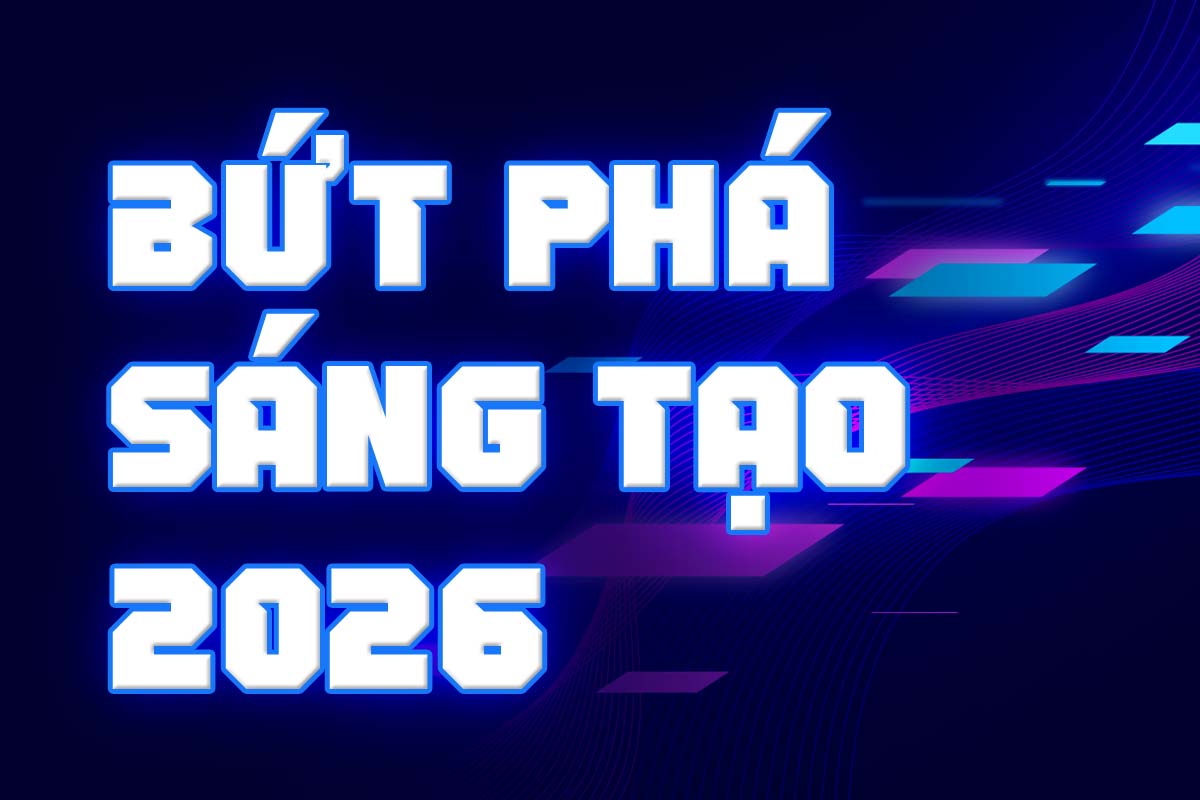
2. TH Geardive - font tốc độ cho fitness, sports và esports gym
TH Geardive có dáng nghiêng, đường cắt sắc và cảm giác tốc độ. Font phù hợp với gym hiện đại, studio HIIT, câu lạc bộ chạy bộ, thương hiệu thể thao, giải đấu fitness hoặc banner quảng cáo có tinh thần thi đấu.
Với TH Geardive, hãy dùng trên nền tương phản mạnh và tiêu đề ngắn. Font có năng lượng cao, nên rất hợp với các thông điệp như "Burn Fat", "Speed Training", "Bứt tốc", "Fit Challenge".
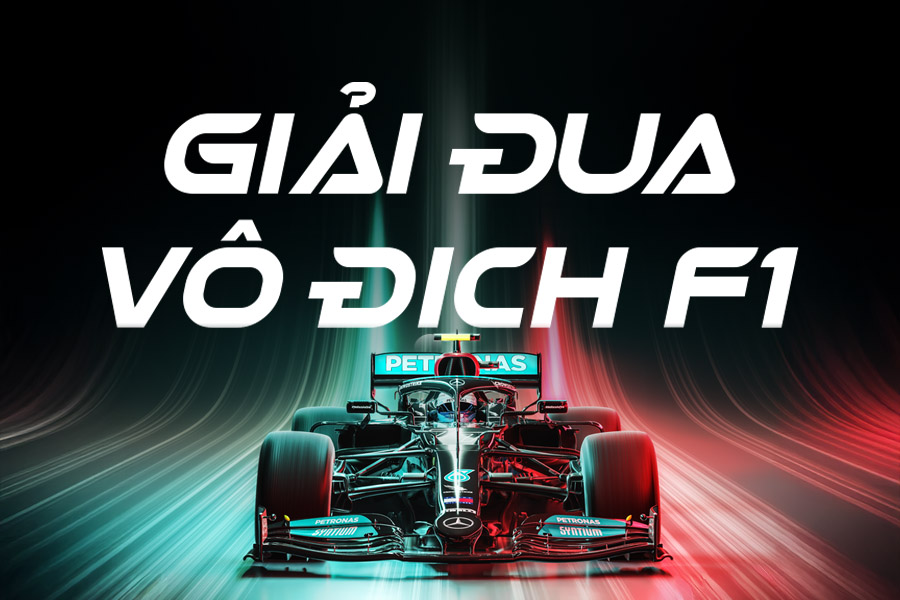
3. TH Glister - condensed cứng cáp cho poster lớp học và banner ngang
TH Glister có dáng condensed, nét dày và gọn, phù hợp khi thiết kế poster lớp học, banner ngang, thumbnail video hoặc bảng lịch tập cần tiêu đề lớn nhưng không có nhiều không gian. Font giúp chữ nhìn mạnh mà vẫn tiết kiệm chiều rộng.
Bạn có thể dùng TH Glister cho tên lớp như "Cardio Burn", "Strength Class", "Boxing Night", "Full Body Workout". Vì chữ nén, hãy tăng khoảng cách dòng nếu tiêu đề có dấu tiếng Việt dày.
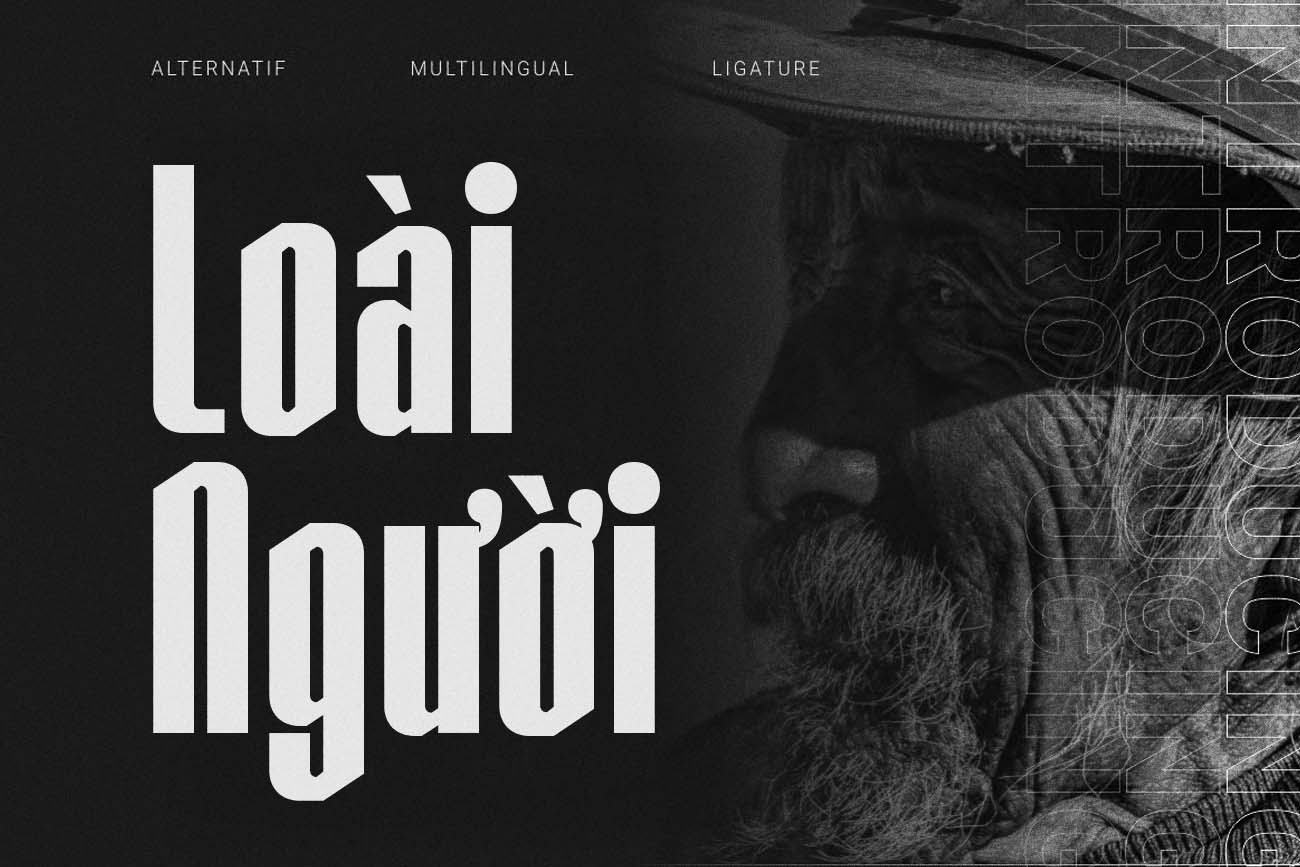
4. TH Infinity - font display cứng cáp cho thương hiệu năng động
TH Infinity hợp với thương hiệu gym, thiết bị tập luyện, sportswear, giải đấu, trung tâm thể hình hoặc các chiến dịch cần cảm giác bền chắc. Font có hình khối mạnh, dễ dùng cho logo chữ, poster và key visual.
Khi dùng TH Infinity cho bảng hiệu hoặc áo thun, hãy giữ bố cục đơn giản. Font đã đủ lực, không cần quá nhiều viền, bóng hoặc hiệu ứng kim loại.
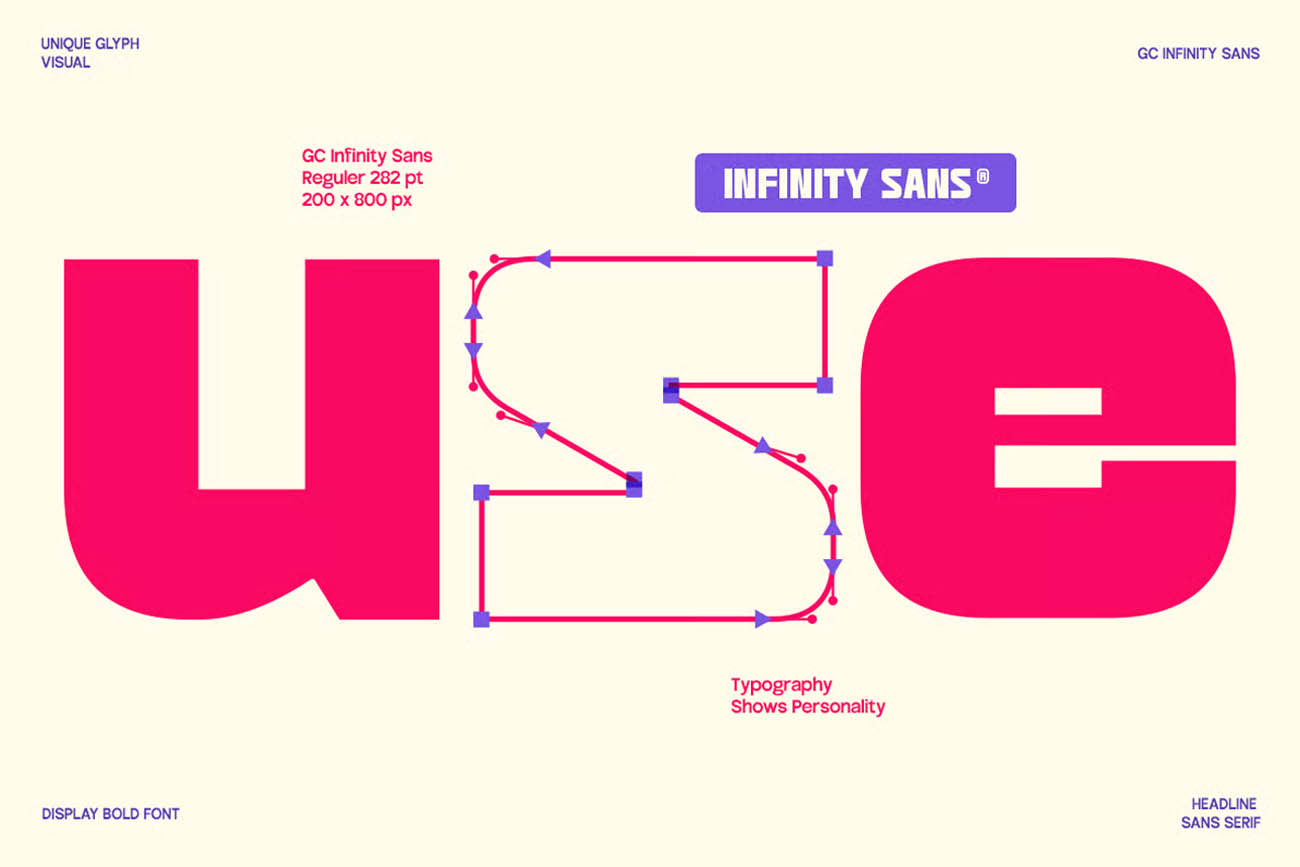
5. TH Army Rangers - stencil cho bootcamp, outdoor và tactical training
TH Army Rangers phù hợp với bootcamp, outdoor training, thử thách sức bền, lớp kỹ năng sinh tồn, thương hiệu tactical fitness hoặc poster sự kiện có tính kỷ luật. Font stencil tạo cảm giác mạnh, nghiêm và khác biệt.
Bạn nên dùng font này cho headline hoặc tên chương trình. Nếu dùng cho toàn bộ lịch tập, font sẽ hơi nặng. Hãy phối với font phụ gọn để thông tin được đọc nhanh.
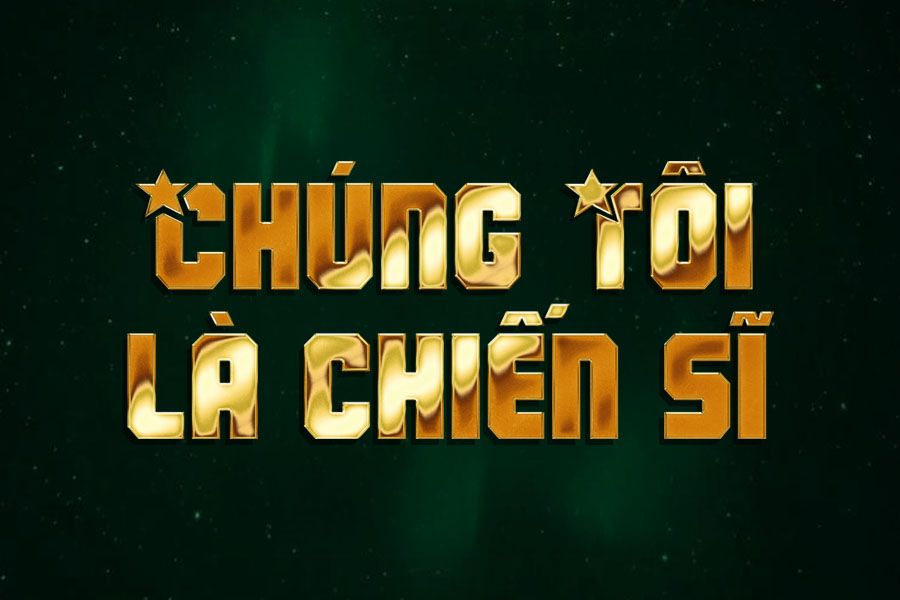
6. TH Jurasick - font thể thao cho hoạt động năng lượng cao
TH Jurasick có cảm giác khỏe, vui và năng động, phù hợp với poster hoạt động thể chất, sự kiện ngoài trời, câu lạc bộ vận động, lớp thiếu niên, giải đấu nội bộ hoặc thương hiệu fitness trẻ trung.
Font này không quá nghiêm như nhóm stencil hay công nghệ, nên hợp khi phòng tập muốn tạo cảm giác gần gũi hơn. Hãy dùng cho headline và phối cùng màu xanh, cam, vàng, đen hoặc các mảng màu năng lượng.
Xem mẫu và tải font TH Jurasick Việt hóa.
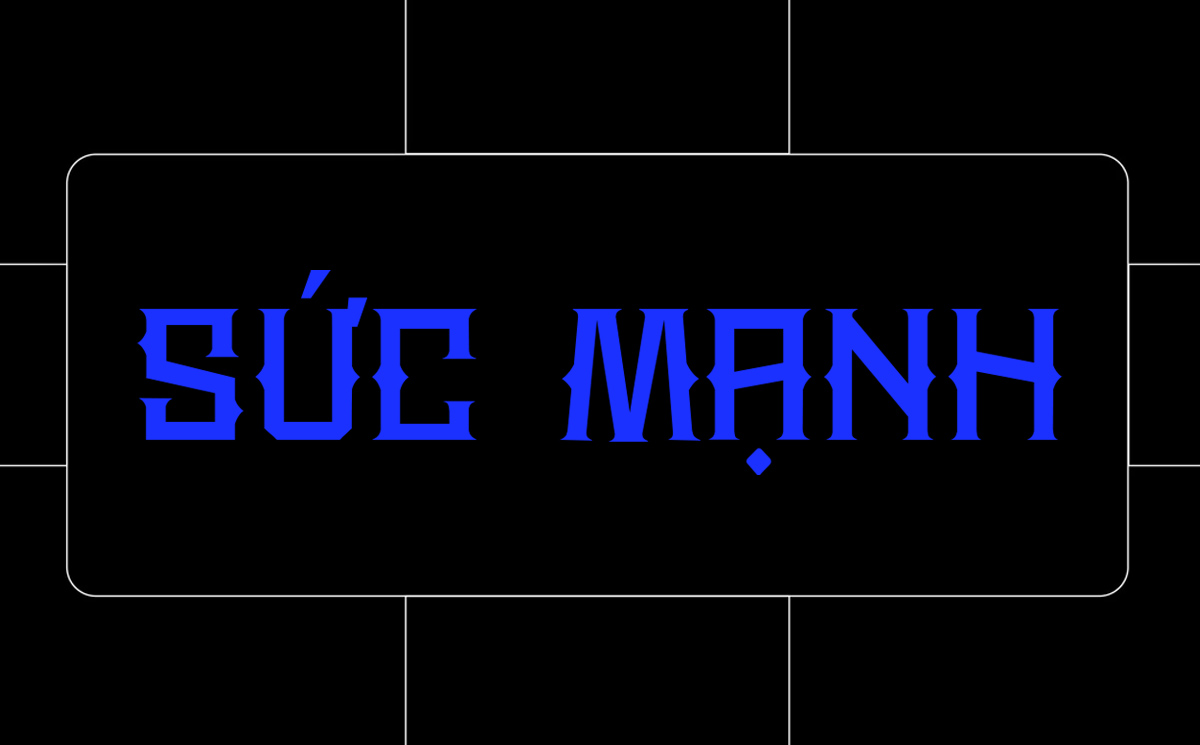
7. TH Cungcap 10 - font game mạnh cho thử thách và giải đấu
TH Cungcap 10 có phong cách game và thể thao mạnh, phù hợp với giải đấu gym nội bộ, thử thách plank, challenge giảm mỡ, poster esports fitness hoặc lớp dành cho nhóm trẻ. Font giúp thiết kế có cảm giác cạnh tranh và hiện đại.
Bạn nên dùng TH Cungcap 10 cho tên event, bảng xếp hạng, huy hiệu hoặc tiêu đề social post. Phần mô tả điều kiện tham gia nên dùng font dễ đọc hơn.
Xem mẫu và tải font TH Cungcap 10 Việt hóa.
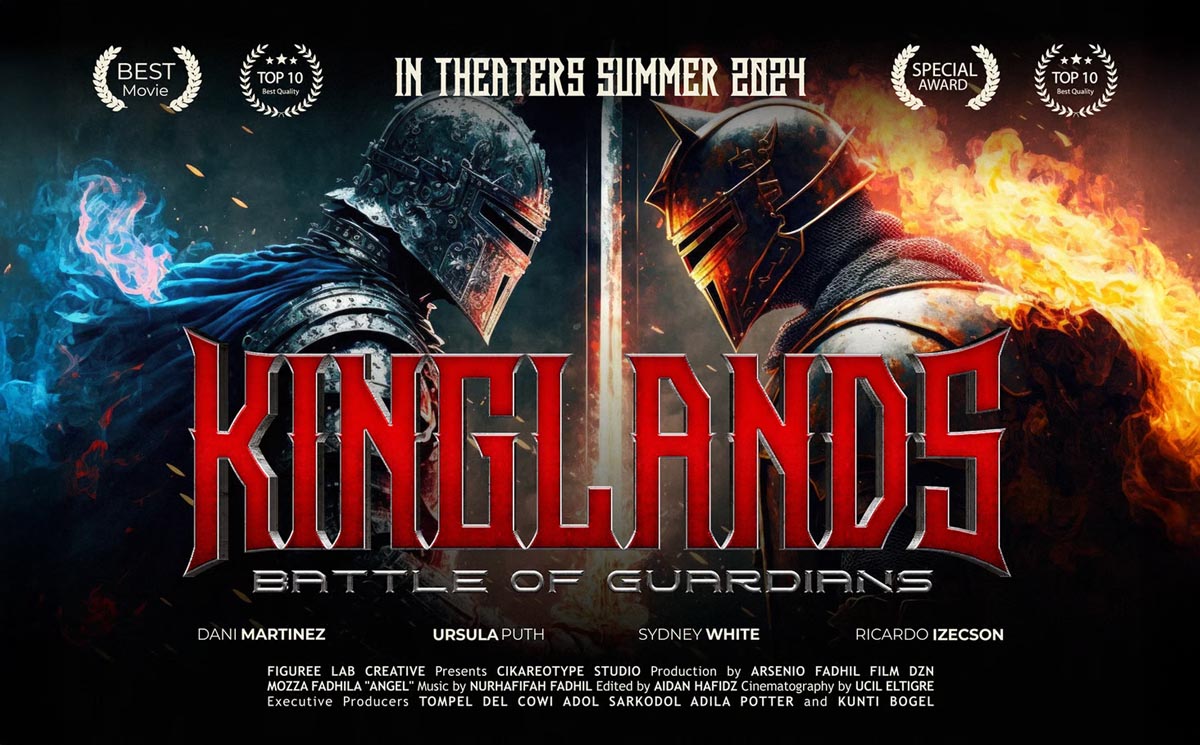
8. TH Gyokz - font công nghệ cho fitness app và phòng gym hiện đại
TH Gyokz hợp với app fitness, phần mềm quản lý phòng gym, smart gym, thiết bị đo sức khỏe, chương trình training online hoặc thương hiệu thể hình định vị công nghệ. Font có cảm giác sắc, hiện đại và tương lai.
Khi dùng TH Gyokz, hãy giữ nền sạch và thông tin gọn. Font này rất hợp với các cụm như "Smart Training", "AI Coach", "Tracking Progress" hoặc "Dữ liệu tập luyện".
Xem mẫu và tải font TH Gyokz Việt hóa.
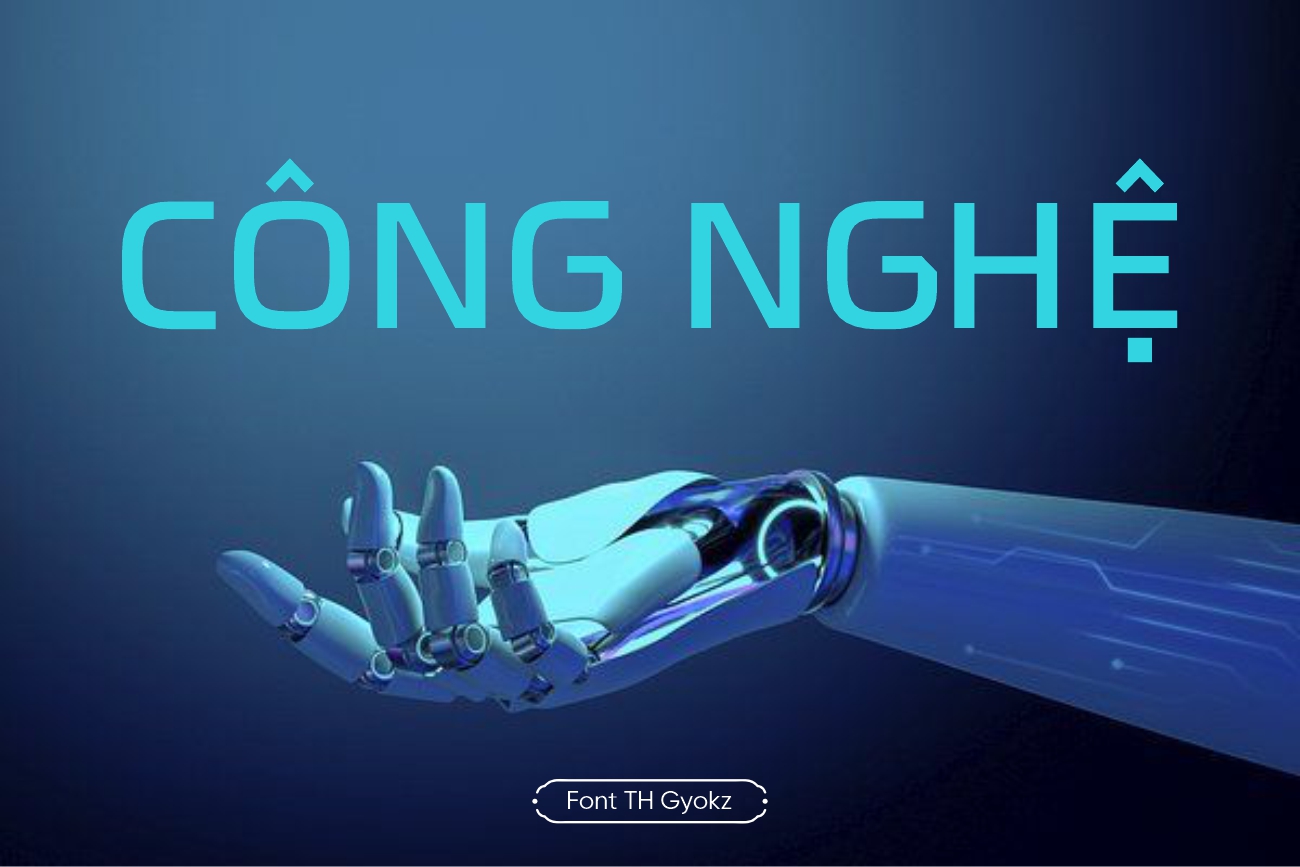
9. TH Seona Display - font digital cho gym online và sản phẩm số
TH Seona Display phù hợp với landing page gym online, khóa học fitness, app tracking, thiết bị wearable hoặc banner digital. Font có hình khối công nghệ, giúp thiết kế nhìn hiện đại hơn.
Bạn có thể dùng TH Seona Display cho headline web, banner quảng cáo và thumbnail video. Với nội dung dài, hãy phối thêm font sans-serif trung tính để tránh mỏi mắt.
Xem mẫu và tải font TH Seona Display Việt hóa.
10. TH Legacy Sans - font phụ rõ ràng cho lịch tập và bảng giá
TH Legacy Sans là lựa chọn tốt cho phần thông tin cần đọc nhanh: lịch lớp, bảng giá hội viên, nội quy phòng tập, form đăng ký, landing page và app. Không phải mọi chữ trong thiết kế gym đều cần mạnh; đôi khi font rõ mới là thứ giúp khách hàng quyết định.
Bạn có thể dùng TH Legacy Sans làm font phụ cho TH Rakend, TH Geardive, TH Glister hoặc TH Kinetic Motion. Cách phối này giúp thiết kế vừa có lực vừa dễ đọc.
Xem mẫu và tải font TH Legacy Sans Việt hóa.
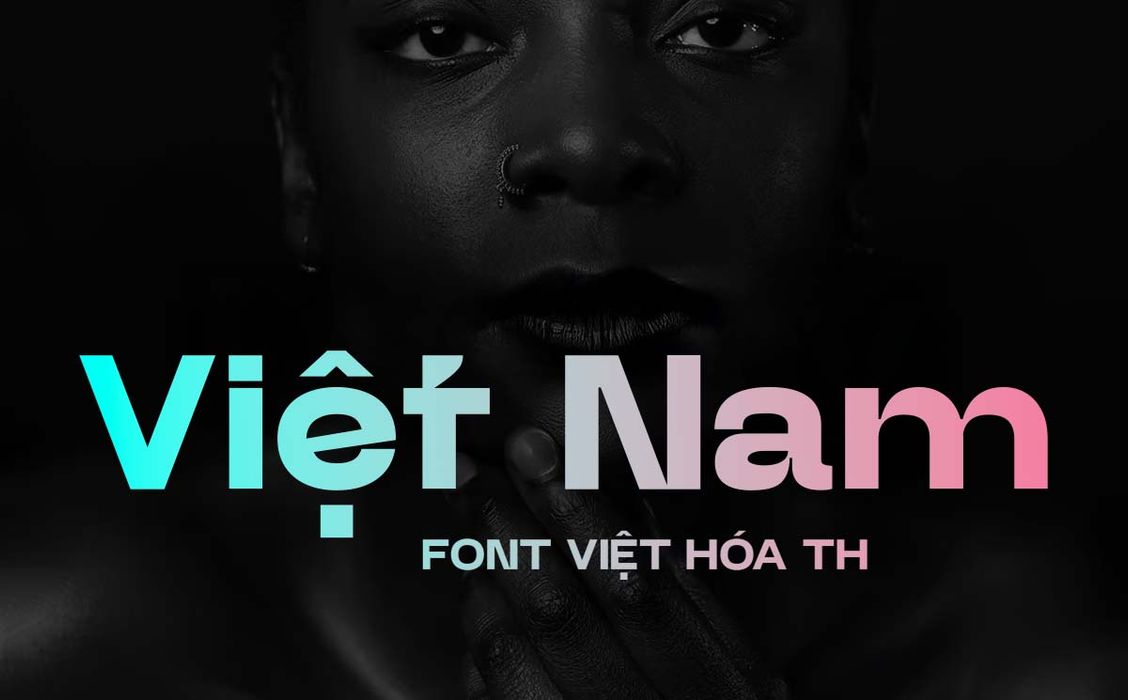
11. TH Guton - bộ font đa weight cho thương hiệu fitness chuyên nghiệp
TH Guton có nhiều style, phù hợp với bộ nhận diện fitness cần hệ thống chữ ổn định: headline, subheading, nội dung, nhãn giá, nút CTA và tài liệu hội viên. Font không quá trang trí nên dùng được trong nhiều ngữ cảnh.
Nếu bạn đang làm brand kit cho phòng gym, TH Guton có thể làm font chính cho hệ thống, sau đó thêm một font display mạnh cho campaign hoặc poster.
Xem mẫu và tải bộ font TH Guton Việt hóa.
12. TH Grotley - luxury sans-serif cho yoga, pilates và boutique fitness
TH Grotley phù hợp với boutique fitness, pilates, yoga studio, wellness center hoặc phòng tập cao cấp cần cảm giác tinh tế. Font vẫn là sans-serif nên đủ gọn, nhưng có sắc thái luxury hơn nhóm font kỹ thuật.
Bạn có thể dùng TH Grotley cho logo chữ, headline website, brochure dịch vụ và bảng giá gói hội viên premium. Bảng màu nên nhẹ hơn: kem, đen, trắng, xanh sage, nâu nhạt hoặc vàng champagne.
Xem mẫu và tải font TH Grotley Việt hóa.
13. TH Retalin Regular - font mềm cho yoga, spa fitness và wellness
TH Retalin Regular hợp với yoga, pilates, spa fitness, lớp thở, thiền, chăm sóc cơ thể hoặc thương hiệu wellness. Font mềm hơn nhóm thể thao mạnh, giúp thiết kế tạo cảm giác thư giãn và thân thiện.
Khi dùng TH Retalin Regular, hãy ưu tiên bố cục thoáng, ảnh sáng và màu dịu. Font phù hợp với headline, tên lớp, quote hoặc banner nhẹ nhàng. Phần lịch tập vẫn nên dùng font phụ rõ.
Xem mẫu và tải font TH Retalin Regular Việt hóa.
14. TH Valoer - font thẩm mỹ cho wellness và lifestyle fitness
TH Valoer phù hợp với wellness, yoga cao cấp, studio chăm sóc vóc dáng, thương hiệu beauty fitness hoặc lifestyle coaching. Font có cảm giác thẩm mỹ, tinh tế và nhẹ hơn các font gym truyền thống.
Bạn nên dùng TH Valoer cho headline, tên dịch vụ, poster lớp đặc biệt hoặc landing page giới thiệu gói hội viên. Với thông tin chi tiết, hãy phối thêm TH Legacy Sans hoặc TH Guton.
Xem mẫu và tải font TH Valoer Việt hóa.
Phông chữ sport tốc độ TH Myahewa Regular
TH Myahewa Regular là một phông chữ sans serif mang phong cách thể thao mạnh mẽ, gắn liền với tinh thần tốc độ, sức mạnh và sự quyết đoán. Với thiết kế hiện đại, đường nét dứt khoát và tỷ lệ chữ năng động, Myahewa mang đến một diện mạo đậm chất hành động – phù hợp cho các dự án branding thể thao, poster sự kiện, banner giải đấu hay giao diện truyền thông liên quan đến vận động.
Xem và tải font TH Myahewa Regular
Gợi ý phối font theo từng kiểu phòng tập
Gym sức mạnh, boxing và bootcamp
Hãy dùng TH Rakend, TH Infinity, TH Glister, TH Army Rangers hoặc TH Kinetic Motion cho headline. Phần lịch tập, địa chỉ và gói hội viên nên dùng TH Legacy Sans hoặc TH Guton để giữ độ rõ.
Fitness lifestyle, PT cá nhân và phòng tập hiện đại
TH Geardive, TH Gyokz, TH Seona Display và TH Guton phù hợp với nhóm này. Bạn có thể tạo cảm giác hiện đại bằng bảng màu đen, trắng, xanh điện, đỏ hoặc cam, nhưng vẫn nên giữ bố cục sạch.
Yoga, pilates và wellness
TH Grotley, TH Retalin Regular và TH Valoer là nhóm nên thử. Với yoga, font không cần quá mạnh. Điều quan trọng là chữ có nhịp thở, khoảng trắng tốt và tạo cảm giác tin cậy.
Checklist chọn font cho thiết kế gym và fitness
- Logo và headline có thể mạnh, nhưng lịch tập phải dễ đọc.
- Kiểm tra font trên bảng hiệu, áo thun, avatar và story mobile.
- Không dùng font quá nặng cho mọi dòng chữ.
- Với font condensed, tăng khoảng cách dòng để dấu tiếng Việt không bị chật.
- Với yoga/wellness, ưu tiên font nhẹ, khoảng trắng rộng và màu dịu.
- Chỉ phối 2-3 font trong một hệ thống thương hiệu.
Font phòng gym Việt hóa cần đúng tính cách thương hiệu. Nếu muốn mạnh, hãy thử TH Rakend, TH Infinity, TH Geardive, TH Glister hoặc TH Army Rangers. Nếu muốn hiện đại và công nghệ, TH Gyokz, TH Seona Display, TH Guton và TH Legacy Sans sẽ dễ triển khai hơn. Nếu làm yoga, pilates hoặc wellness, TH Grotley, TH Retalin Regular và TH Valoer sẽ tạo cảm giác tinh tế hơn.